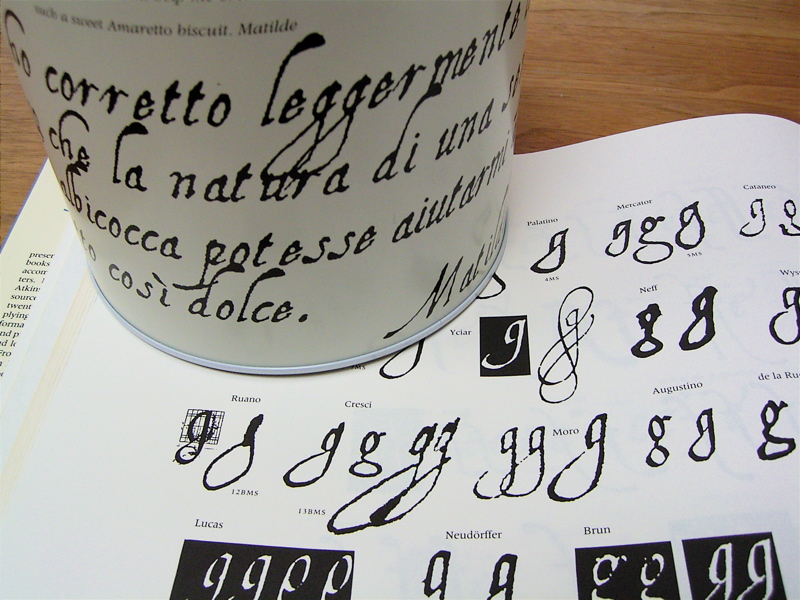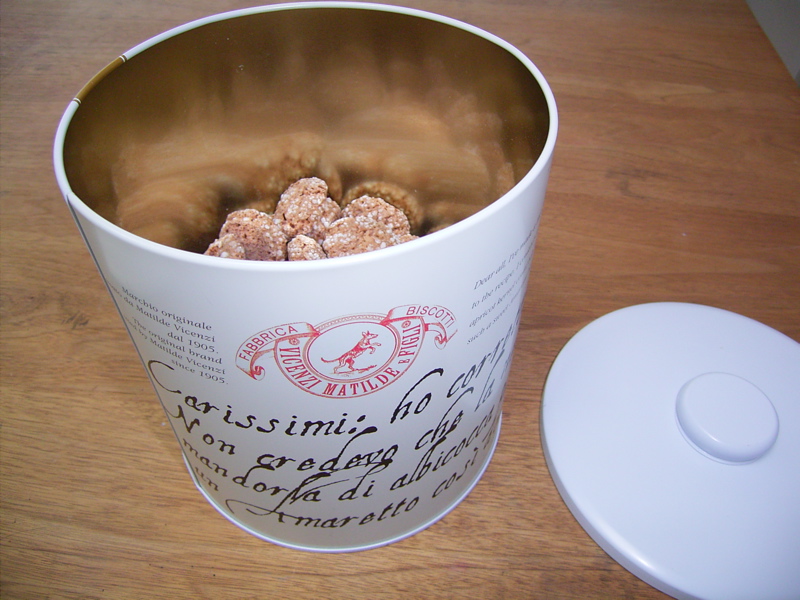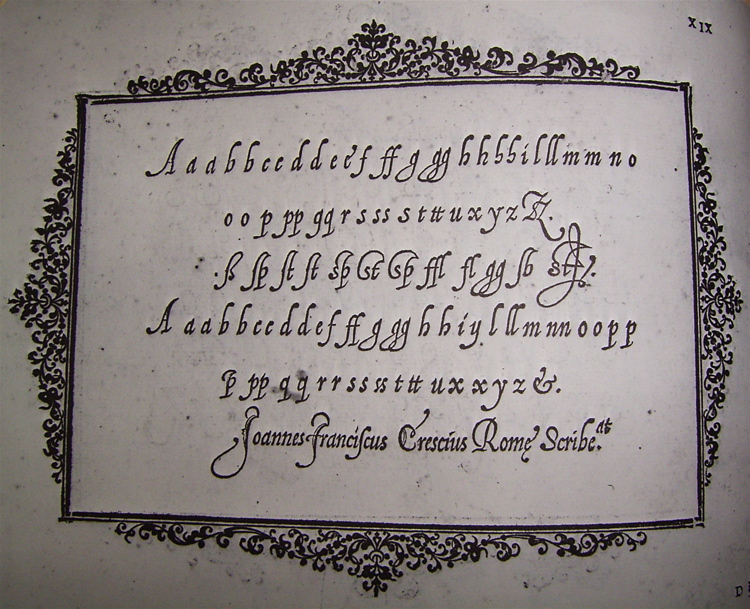
Calligraphic Painting
渡辺美恵子さんと和田祐子さんの二人展が開催されています。
言葉を描く自由なカリグラフィーの世界を探求されているお二人の作品展です。
初日の昨日、さっそく行ってきました。
和田さんの作品は赤茶色と黒で構成されていて、下地のテクスチャーや線の面白さが際立っています。絵の具、下地、道具はカリグラフィーではあまりポピュラーではない物を使っていますので、長い間いろいろと試して来てここまで到達したんだろうなぁ!と感慨無量です。そしてその過程を実に楽しんでいることがよくわかります。存在感のある線によって出来る画面には緊張感があり、鑑賞者に非常に多くの事を語りかけてくる作品です。
渡辺さんの作品は、デザインの完成度は言うまでもなく、色と書体とそして文章の内容がひとつとなり、素晴らしい世界を構築しています。一 体何を使って、どうやって、そしてどの順番で作ったのだろう?とすべての作品に思うほど、非常に時間をかけて作り上げています。文字の確かさがあるからこ そ、そこを超えたところにある「自由」を楽しめるのだなぁと改めて感じ入りました。カリグラフィーの楽しみ美しさをすべてを持ち、深く鑑賞できる本当に質 の高い作品の数々でした。
この作品展のタイトルにあるように、「自由に言葉を描く事ができるカリグラフィー」は、きっとどの人たちにとっても理想だと思いますが、そこに力む事なく到達しているお二人の成果に、日本のカリグラフィーのレベルも非常に高くなっていることを確信した一日でした。
ペンケース
カリグラフィーのペン先は取り外しができるので、ホルダーとペン先は別々に持ち歩いたり保管したりする事が多いのですが、普通はジャラジャラとケースに入れてしまいます。
しかし、この画像のペンケース!見た時には驚きました。
これはクラスに通っていらっしゃるK子さんのもの。もちろん手づくりです。表の金箔とアルミ箔が貼ってある紙から手づくりなんです。
ひとつひとつのペン先が入っている部分は、そう段ボールで出来ています。なんというアイデアでしょう! これがまたペン先のサイズにピッタリ!しかも折りたたみが出来るという優れもの。
一体、最初は誰のアイデアだったんでしょうか。段ボールの断面を見た時にペン先を差し込んでみようと思ったその頭の柔軟さに脱帽で〜す。応用すれ ば他にも使えるかもしれませんね。そうそう、段ボールのような紙で、もっと堅くて色付きのペーパーがありましたよね。名前なんだっけな?
バレンタインデーカード
今年のバレンタインデーのカードは、昨年のクリスマスカードに引き続き盛りだくさんなものになりました。
フォルダーはトレーシングペーパーです。あまり厚いとバリバリしますので50gぐらい。そして中身は、パンチで抜くも良し、水彩絵の具でwet in wetも良し。切ったり貼ったり結んだり、シールやリボンやスタンプも大活躍。このごろはハートのパンチもいろいろな形が出て来て、子供っぽくなりすぎず に使えるので嬉しいですね。
こまごまと小さなハートを一杯詰めて、ひとつひとつ何が出てくるかお楽しみカードです。形と素材がいろいろある方が楽しいので、アイデアも尽きる事がありません。ハートで花輪のデザインは生徒さんのアイデア!気に入ってます。
トレーシングペーパーを通して見える色としては、赤よりもピンクの方が色味もよく綺麗に見えます。(赤だと沈んでしまいます)フォルダーの形は可愛い感じにしたいので、畳んだときに正方形に近い形にしました。
もし、これでは甘すぎ!と思うなら、色とフォルダーの形を変えればグッと大人っぽいのも可能です。黒とピンク、シルバーと赤、または赤と茶色の組み合わせとか・・・・
今回使ったひもやリボン、毛糸類は「Fanky with fibers」のパステル色を買いました。なんと12種類のいろいろな毛糸(りぼん)が一緒にひと巻きになっています。ほ〜んと可愛いんです。
アマレッティとライティングマスター
アマレッティというアーモンド風味のビスケット(イタリアのお菓子)の素敵な缶入りをみつけました。
この大きな缶の外側の文字! ルネサンス時代の書家の文字!なんて素敵!家へ帰って中身をポリポリ食べながらよく見たら、なぁ〜んだ、活字!今は良く出来たのがあるんですね。
でも、どんなWriting Master(書家)の文字からこの活字が出来てきたのか知りたくて、「Masters of the Italic Letter」という22名の書家の書いたサンプルが載っている本を調べてみました。
どうもCresciと言う人の文字に大変似ています。缶の一行目の小文字のgが続いた形と、下の本のggを見比べて来て下さい。似てるでしょ!? アリッギやカタネオやルーカスといった名前は有名でよく目にしますが、この人の文字をじっくり見たのは初めて。
この本の説明を読んでみました。彼は生徒に文字を教える時、どうしても書けない生徒には、生徒の右横に座り、彼の左手でペンを持つ生徒の右手を持ち、彼自 身が右手で書くのと同時に手を添えた左手でも一緒に書いて教えたのだそうです!すご〜い!!この指導方法は細かいところや手の動きがはっきりわかって有効 的だったそうです。
いやいや、さすが!です。
それにしてもこの書体はなんという活字なのでしょうね。どなたかご存知ですか?
外味だけでなく、この中身のビスケットも素晴らしいです。甘さ控えめで香りもよく、後をひく美味しさです。結構沢山入っていて¥1.000。クィーンズ伊勢丹で売っていました。
鳥の図鑑
鳥インフルエンザですっかり嫌われ者になってしまった鳥たち・・・先日のセンター試験では木に戻ってきた鳥の鳴き声がリスニングテストの邪魔と、こちらでも嫌われていましたね。
でも鳥の姿を眺めるのはいいものです。
先日依頼を受けて書いたカリグラフィー作品に、どこかにハトの姿を入れなくてはならなくて・・・
うーん、でもハトなんて描けない・・・飛んでいる姿はどんな?とあたりを見回してもハトは見つからない。
そこで、図鑑の出番です。写真の図鑑もいいですが、これもよいですよー!
野鳥の図鑑―にわやこうえんの鳥からうみの鳥まで
とってもとってもきれいな薮内正幸さんの絵です。本当に活き活きしています。
巻末には鳥の歩き方、飛び方、餌のとり方、などもまとめてあっておもしろいです。
この図鑑のおかげで作品も書きあがり、ほっとしたのでした。
冒険者たち―ガンバと15ひきの仲間
ところで薮内さんを最初に知ったのは斉藤惇夫「冒険者たち」という物語に夢中になったときです。斉藤さんのお話にもワクワクしましたが、挿絵もぴったりで気に入っていたのです。
むかーしテレビアニメにもなりましたね(ガンバの冒険)アニメのほうは悪役のイタチの絵がほんとにコワカッタ!
アルファベット・ディスク
何だか気になる・・・でも何のために使うのかわからない・・・。
そんな代物をIDEE SHOP(二子玉川店)で見つけました。
これだけは日本語の説明がなく(なんで〜)、しょうがないので裏面を読みながら・・・36枚のディスク状のアルファベットで、文字はvictorian wood typeからおこしたものと判明。なかなか凝っていますね。
絵本の中の住人
いつもはこども部屋にあるぬいぐるみたち、棚を片付けしている間ちょっと移動してきました。
ホコリもたまには払わないと・・・ときどき投げられたり、お店ごっこの商品にされているのでかなりお疲れ。